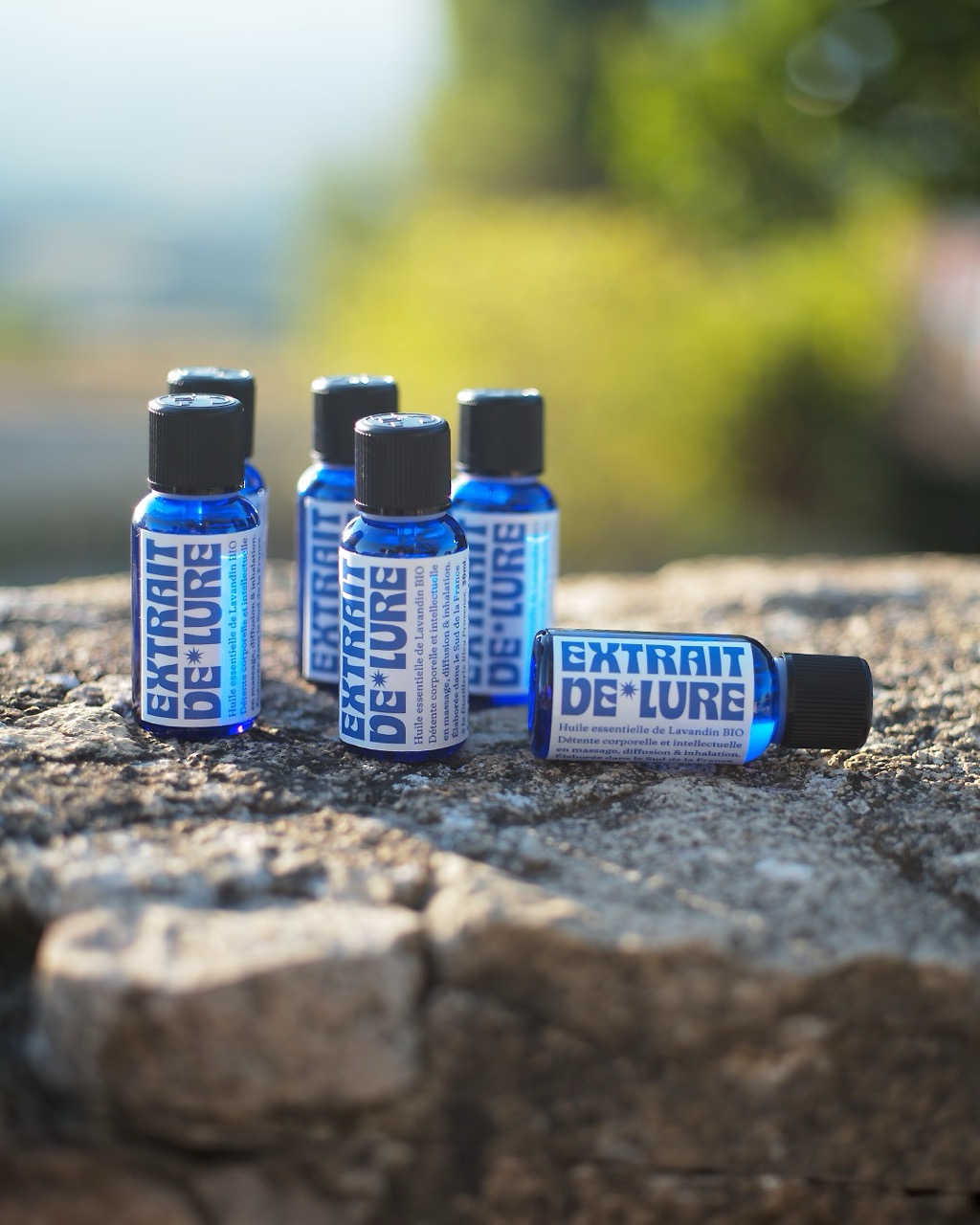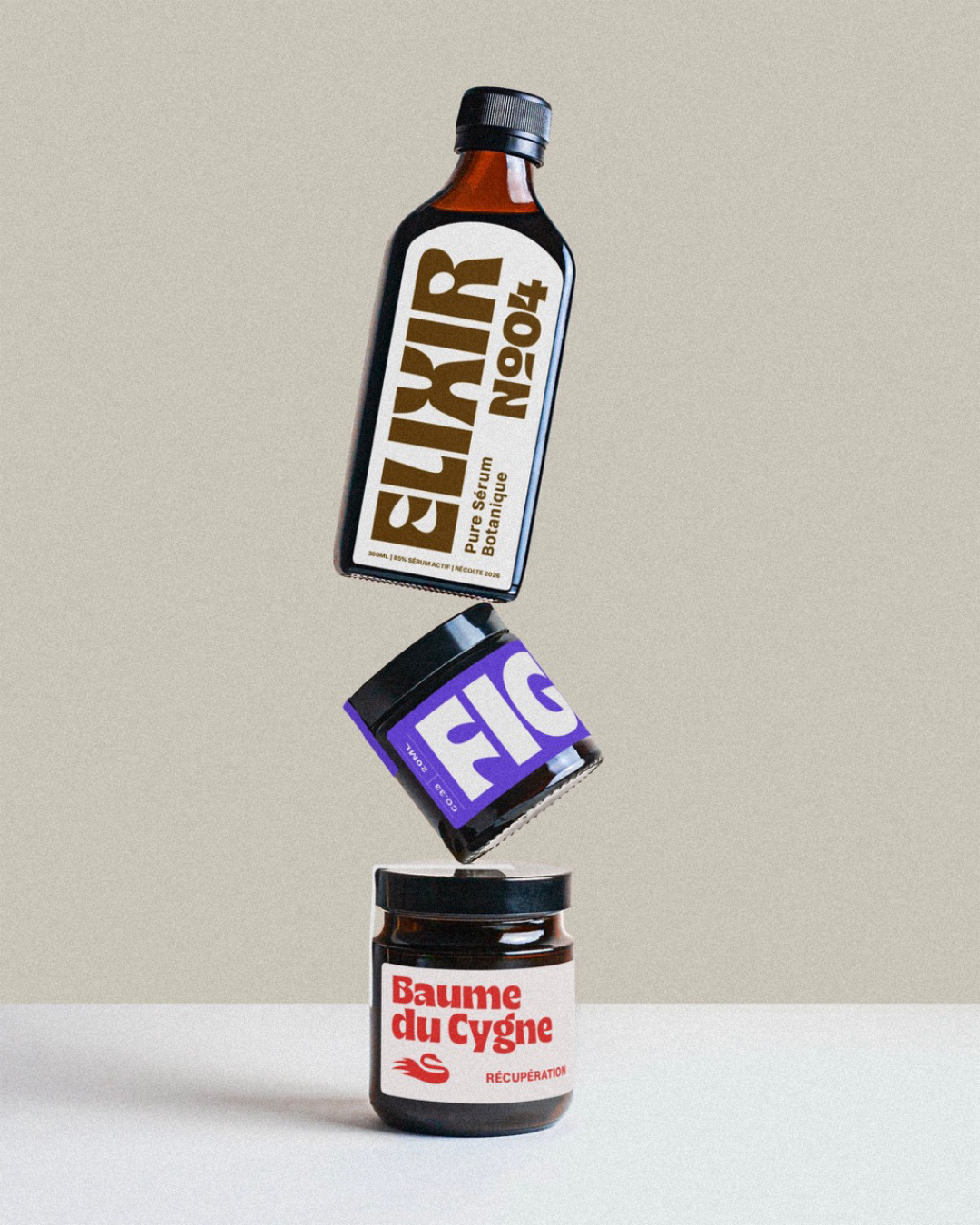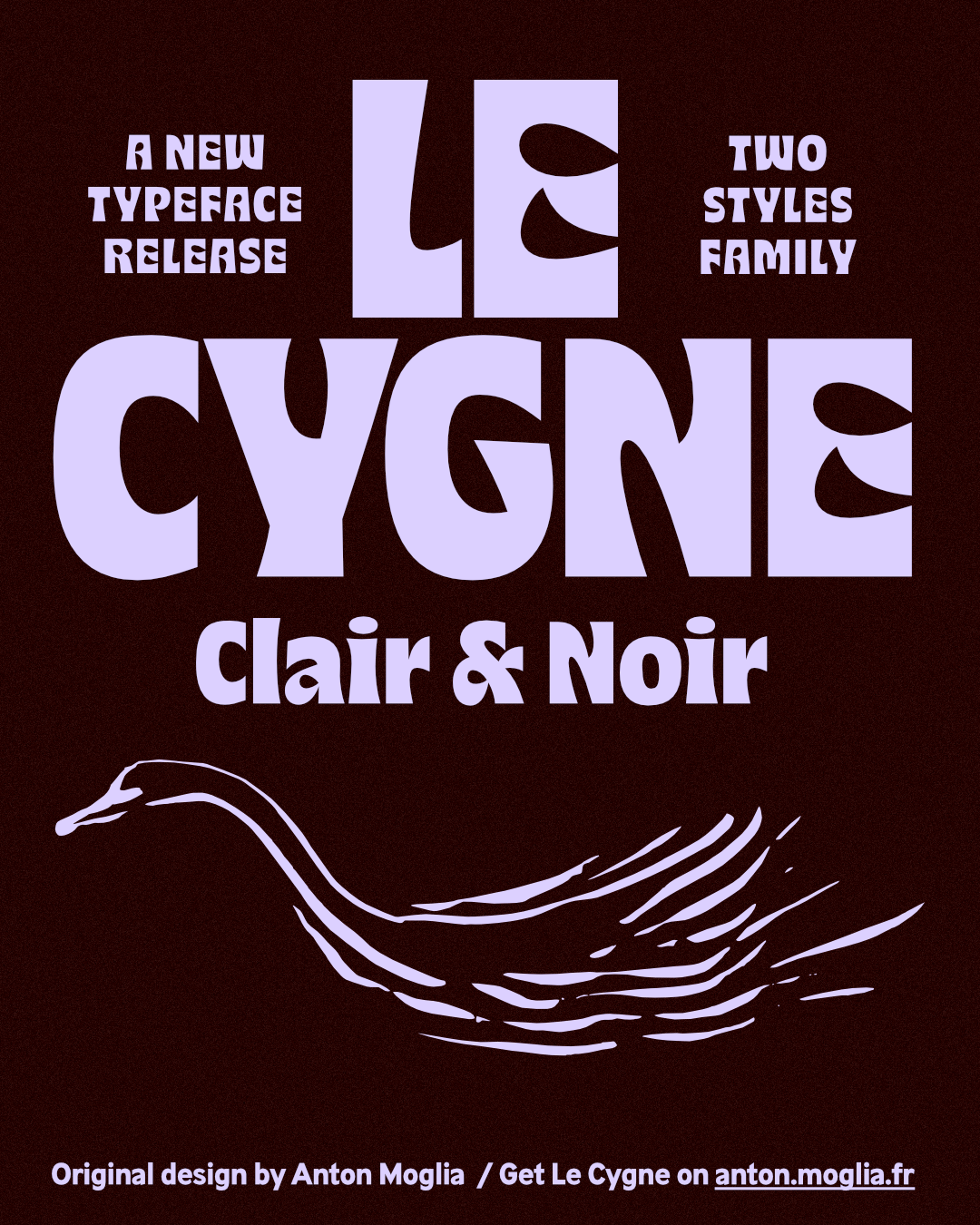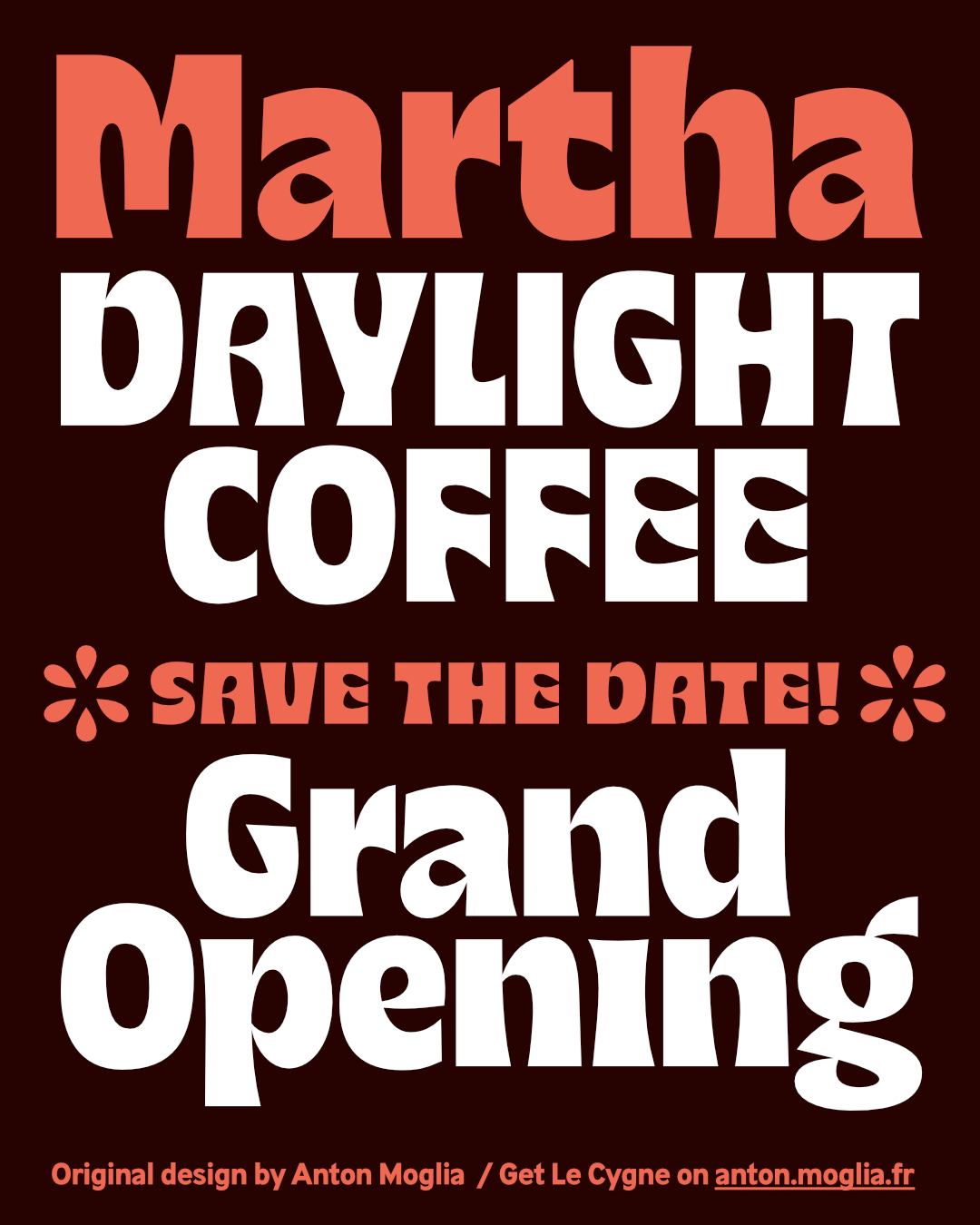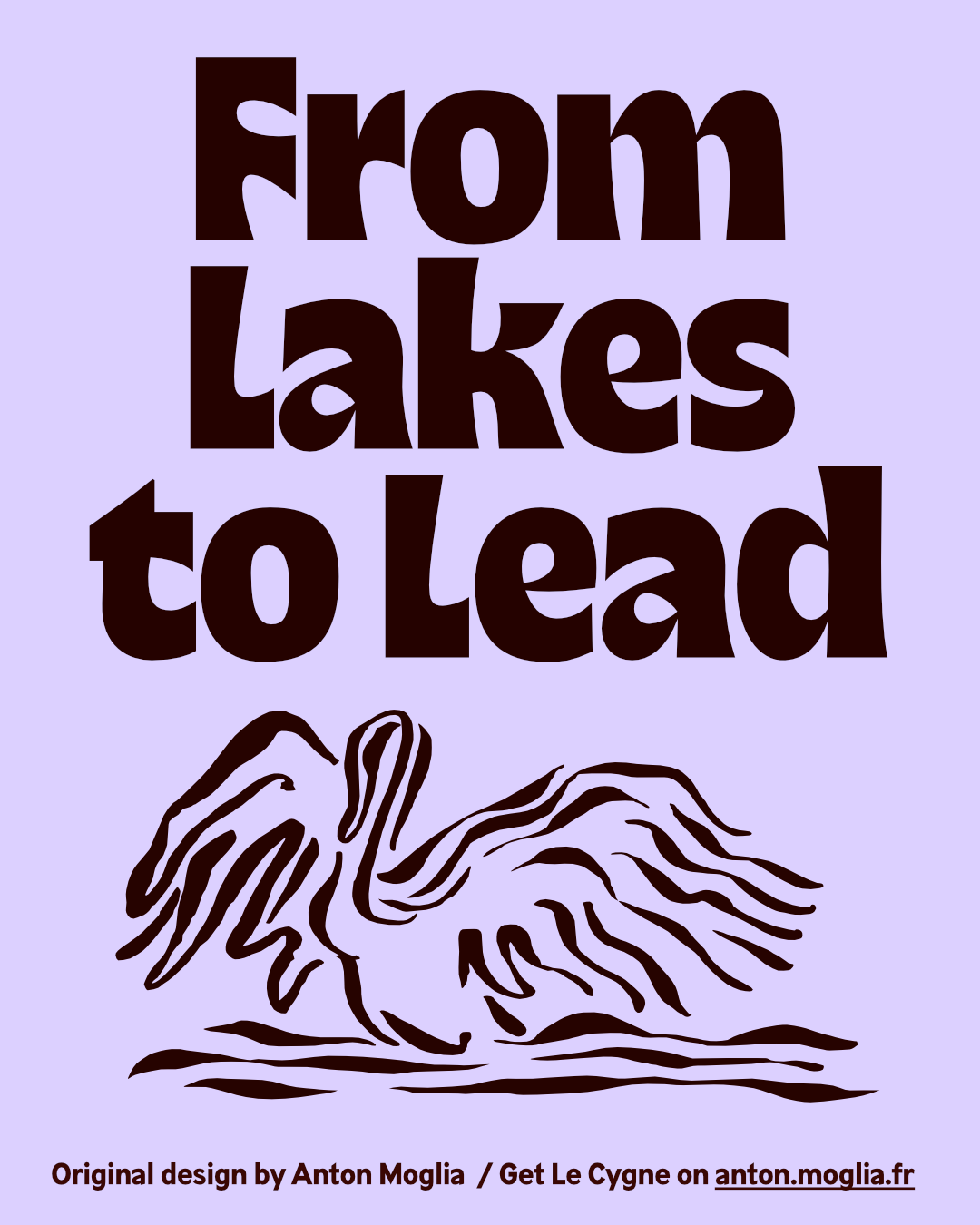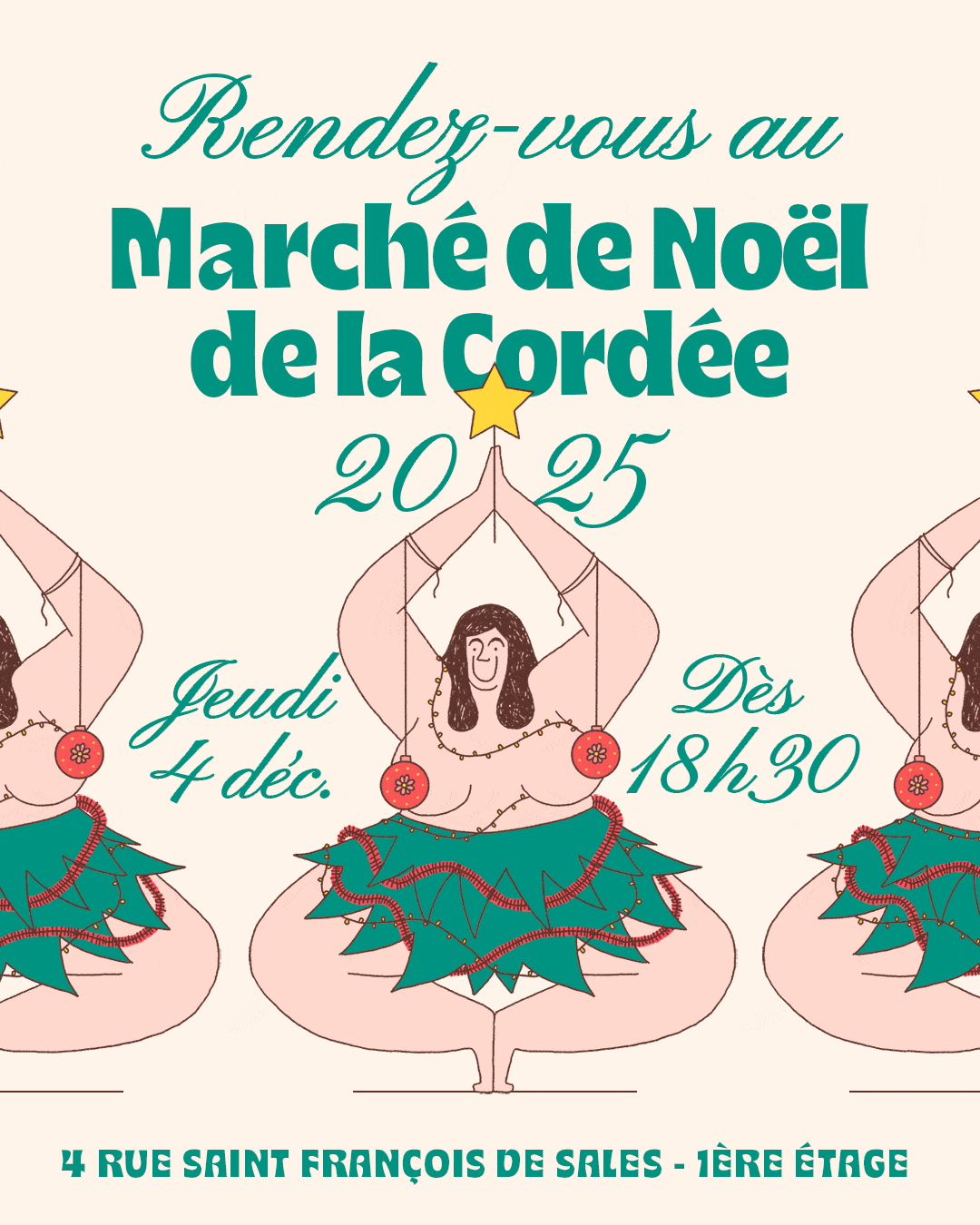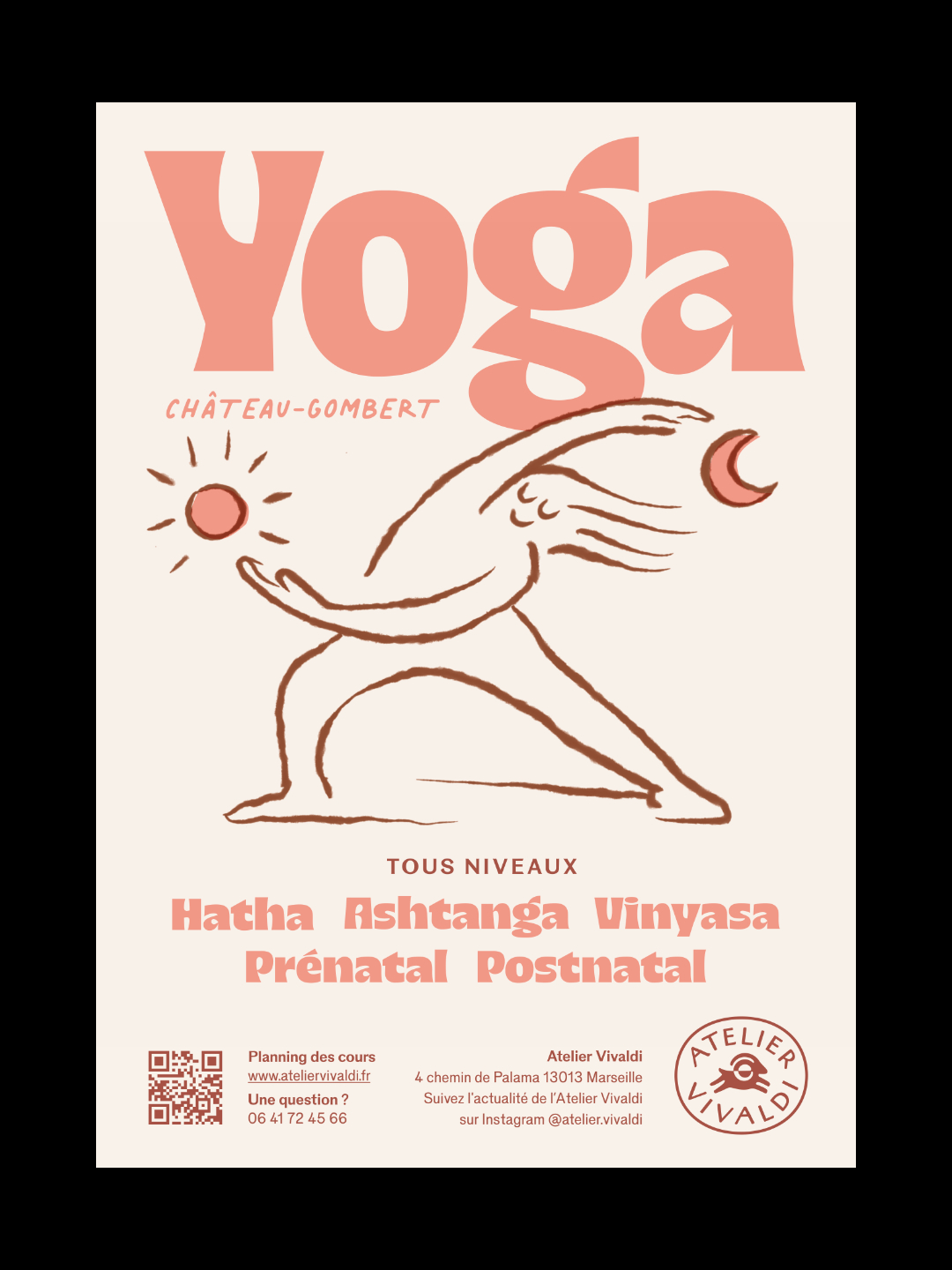
Le Cygne
2 styles, Clair & Noir
Le Cygne — Clair
Le Cygne est une police de titrage très grasse et compacte. C’est une Antique inspirée des formes humanistes, avec un dessin tranchant et organique. Elle permet de créer des blocs de texte très noirs et réguliers.
J’ai vu un cygne faire le moonwalk aux championnats de zouk acrobatique.
Le Cygne — Noir
Un cygne bravache pique mes corn-flakes pendant que je zone aux wc.
Comparaison des styles
Aa
Clair
Aa
Noir
Cygne des Alpes
Nom Le Cygne
Styles Clair, Noir
Langues supportées Support linguistique Latin Occidental (Western European). Couvre les principales langues d’Europe de l'Ouest et des Amériques.
Le Cygne est une police de titrage très grasse et compacte. C’est une Antique inspirée des formes humanistes, avec un dessin tranchant et organique. Elle permet de créer des blocs de texte très noirs et réguliers.
Designer Anton Moglia